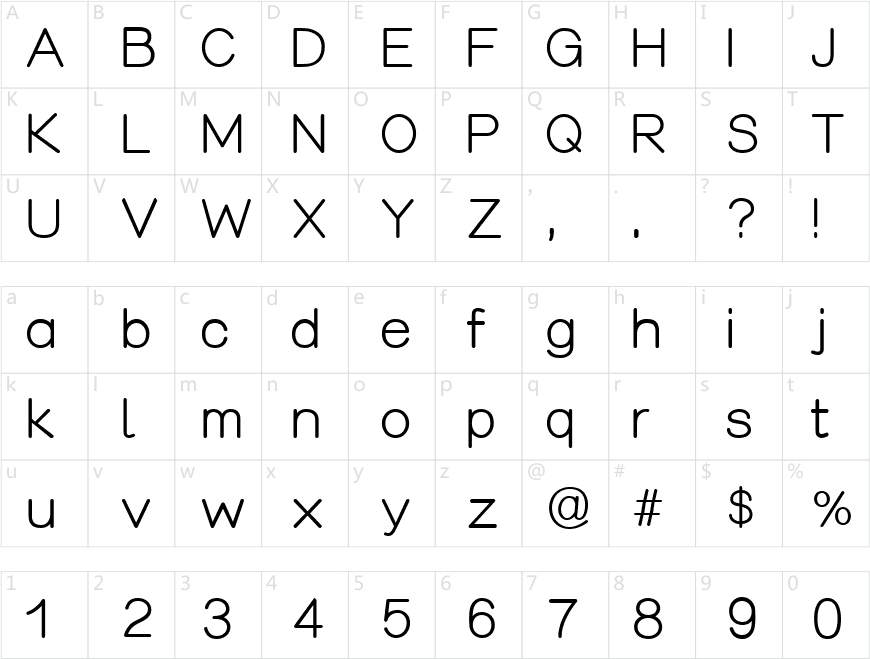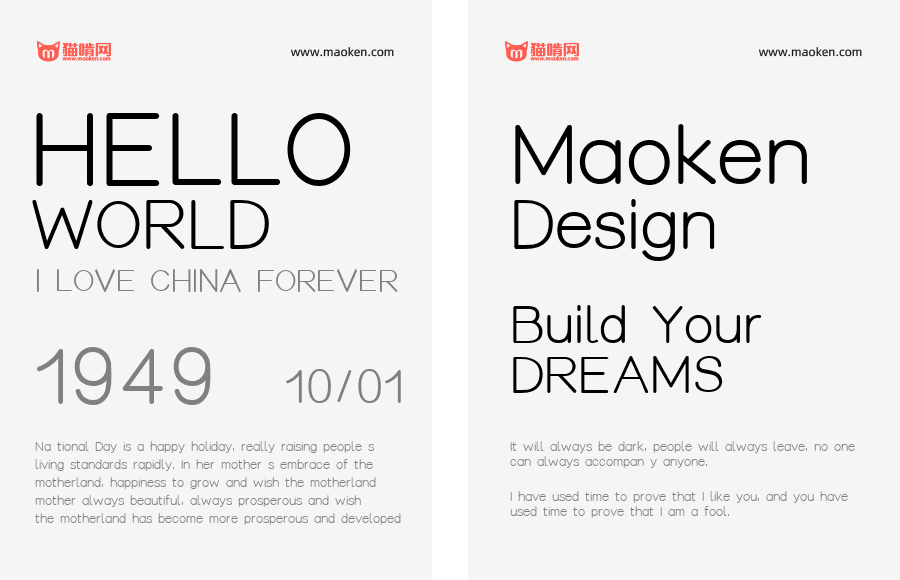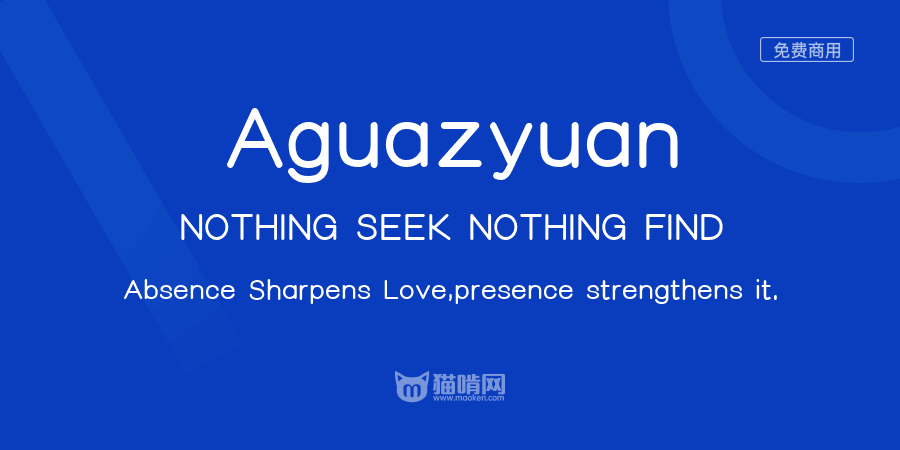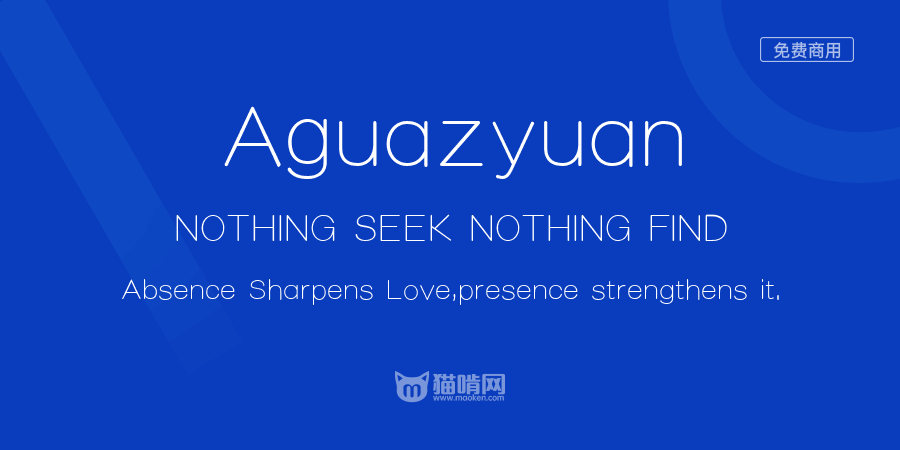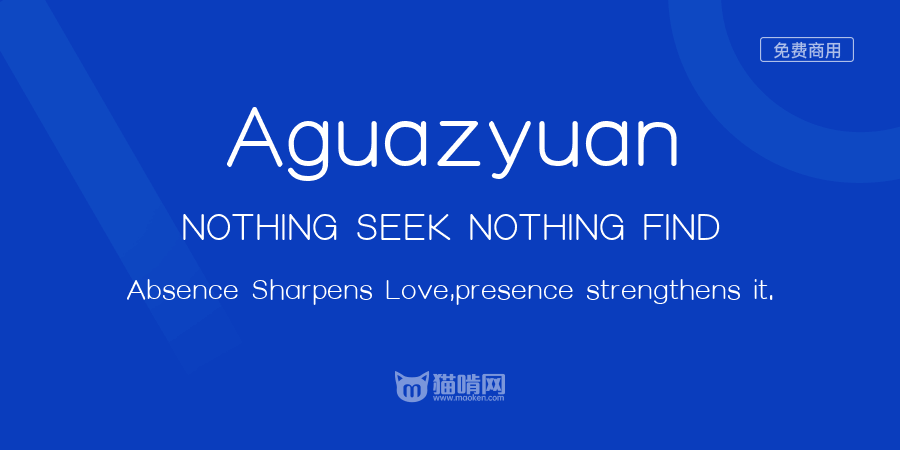
Aguazyuan
Diligence climbs; perseverance sails.
Aguazyuan NOTHING SEEK NOTHING FIND Absence Sharpens Love, presence strengthens it.
设计师的话:
入行至今已有五年时光,一个偶然机会在网上看到了设计师卢帅的字体设计教程,刚开始是惊讶,后来是喜欢,再后来就是疯狂喜爱,终于如愿成了卢帅老师的学生。很幸运,在卢帅老师这里,我学到了很多设计方面的技术和本领,同时也学习了老师的为人之道,教学初心…
想说的话太多了,我又不是很擅长表达,那么,就不多说了。
我们进入正题吧。
2020年9月份一整月,开发了阿瓜准圆体【Aguazyuan】,共三款字型,本套英文字库终身免费商用,本款字体非常适合大篇幅英文正文出现,良心力作,祝愿设计师同行小伙伴们多多升值【升职】,多多加薪【赚票子】
When you are old and grey and full of sleep, And nodding by the fire, take down this book, And slowly read, and dream of the soft look Your eyes had once, and of their shadows deep; How many loved your moments of glad grace, And loved your beauty with love false or true, But one man loved the pilgrim soul in you, And loved the sorrows of your changing face. And bending down beside the glowing bars, Murmur, a little sadly, how Love fled And paced upon the mountains overhead And hid his face amid a crowd of stars.